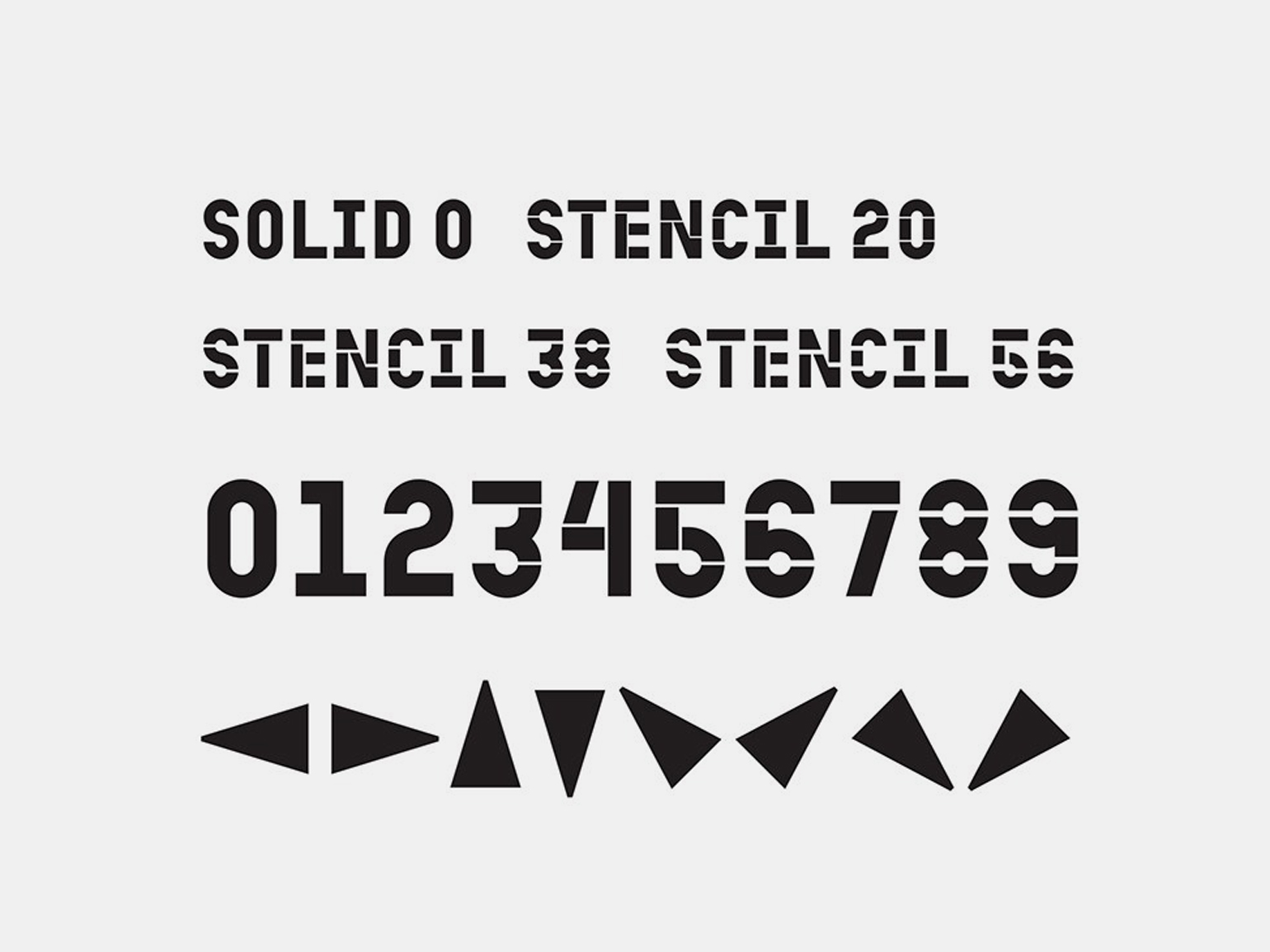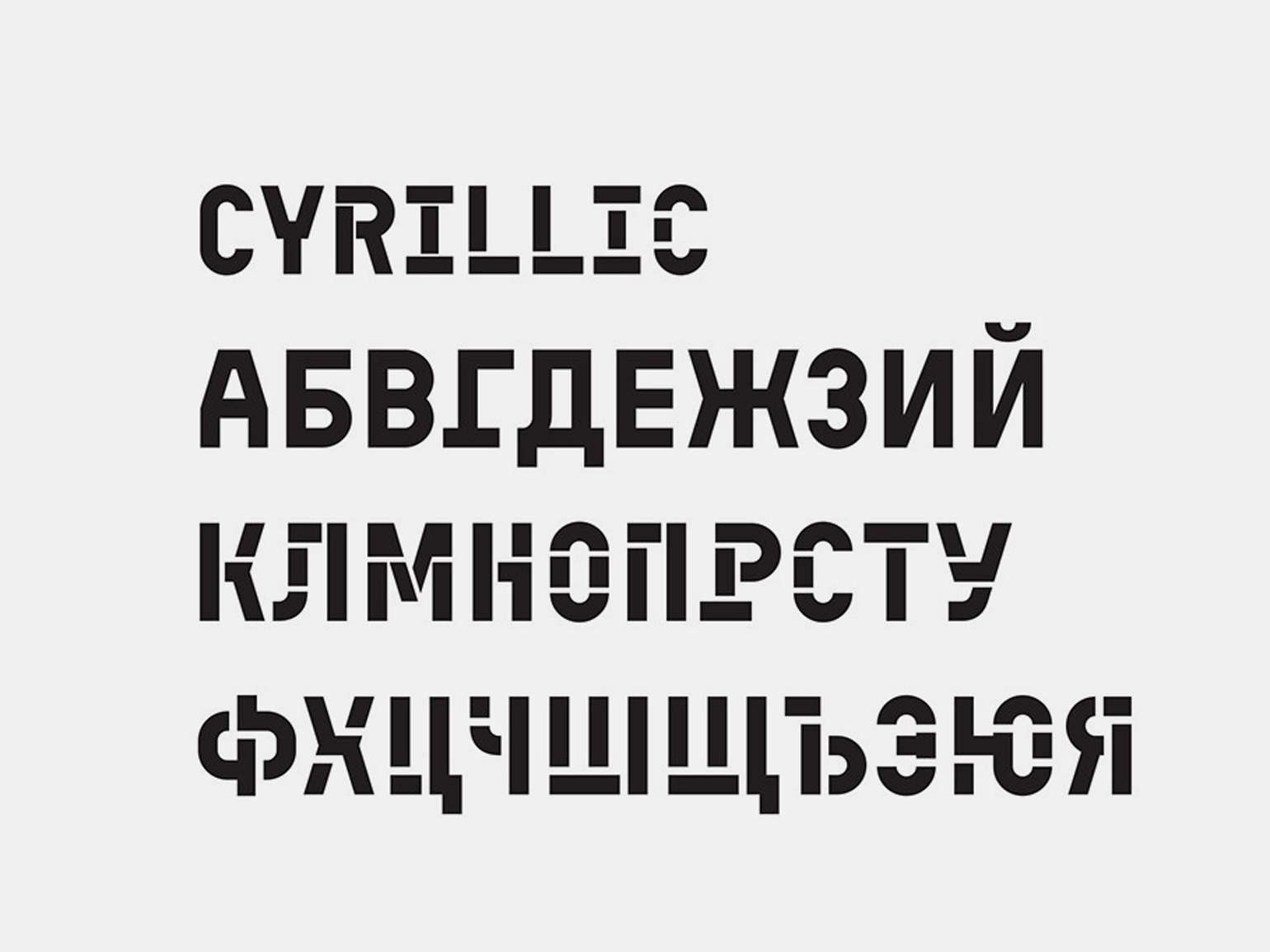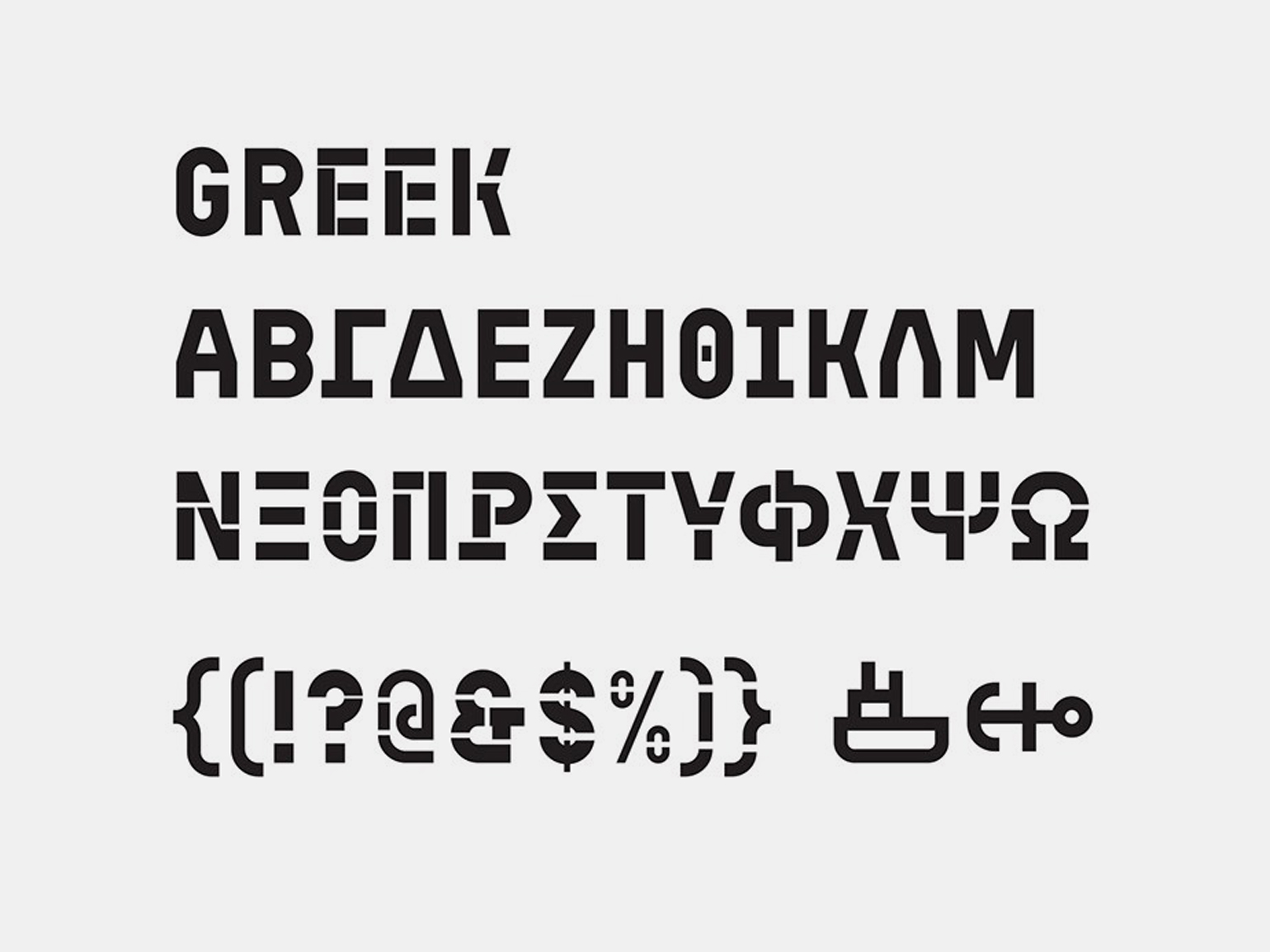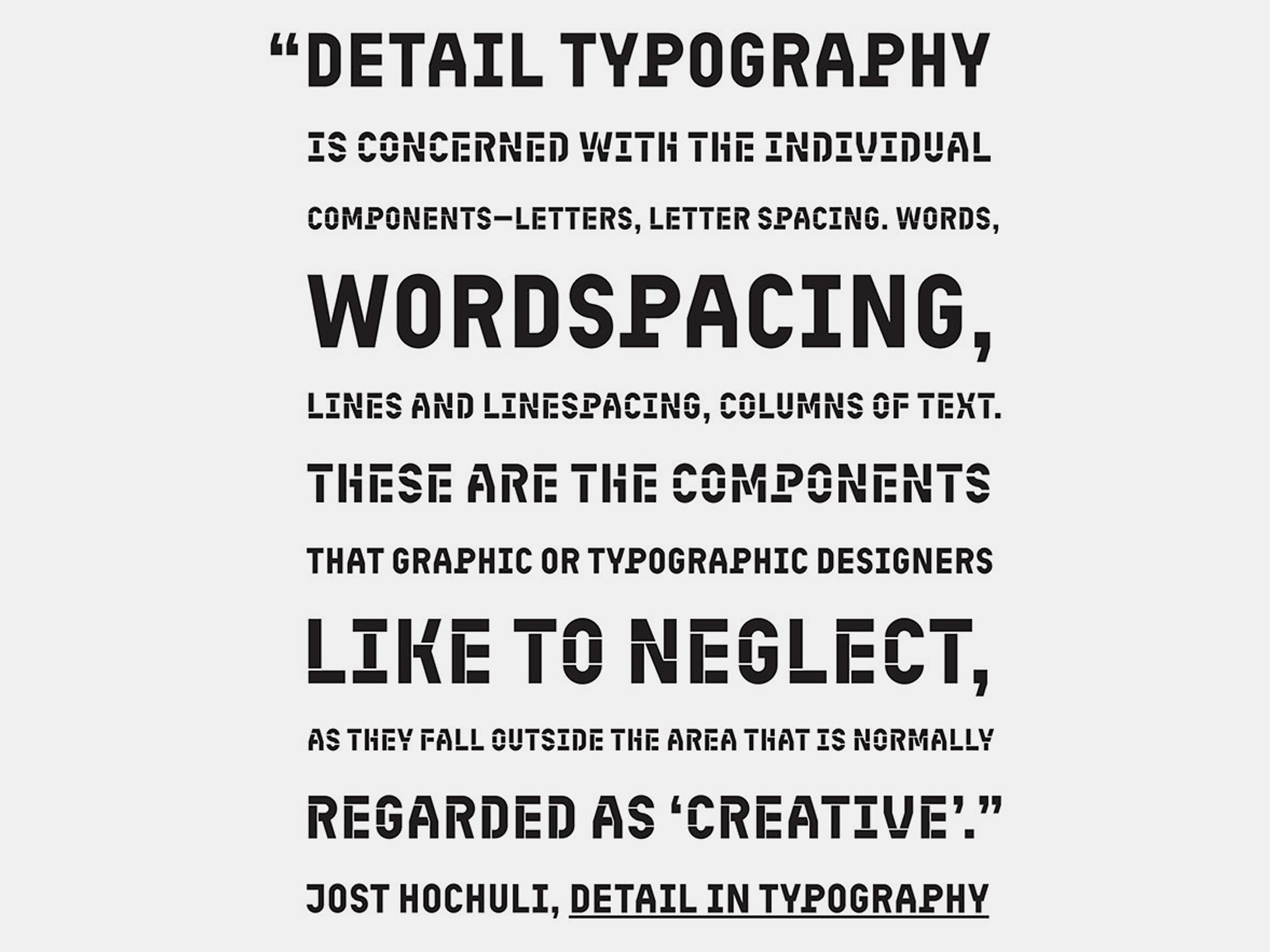
Шрифт Kabeltouw студии CoFo стал лауреатом премии Communication Arts
Он напоминает о мореходном деле и трафаретных надписях на контейнерах и буксирах.
Communication Arts — крупнейший международный дизайнерский журнал. Он был основан в 1959 году. Ежегодно Communication Arts проводит конкурс в шести категориях. Одна из них — типографика. В 2024 году в список лучших шрифтовых работ вошёл шрифт ​​студии Contrast Foundry. Мы попросили рассказать о нём его создателя Егора Головырина.
«Мне нравится относиться к шрифту как к материальной, а не как к цифровой вещи. Даже заведомо диджитальный проект я начинаю с каллиграфии, маркерного рисунка или вырезания из бумаги. Так же получилось и с Kabeltouw. Мне нужны были трафаретные формы для вывески. Я вырезал три картонных модуля: полукруг, прямую и диагональ — и сложил из них все нужные буквы.
CoFo Kabeltouw
В шрифтовой редактор „Кабельтов“ попал, когда я работал над своим дипломным проектом в Полиграфе (Московский Политех. — Прим. автора), книгой „Горизонт“ о морской терминологии, узлах, сигнальных флагах.
В качестве основного рабочего шрифта я сразу выбрал William Text Pro Марии Дореули, но хотелось поддержать красочные оттенки и плёночные фотографии яркой шрифтовой графикой. Тут я и вспомнил про свою тогда ещё безымянную трафаретную кассу. Пазл сложился: на морских контейнерах, предупреждающих знаках, буксирах очень часто можно увидеть такие брутальные буквы. Металл, краска, цвет — всё что нужно!
CoFo Kabeltouw
Позже добавилось второе начертание, монолитное. Уже в рамках работы в CoFo я добавил шрифту вариативность, чтобы дизайнер мог выбирать ширину трафаретных перемычек, нужную для дизайна и масштаба макета.
Я редкий участник конкурсов, а Kabeltouw — первый из моих выпущенных в свободную продажу шрифтов, так что в этот раз всё очень здорово совпало.
CoFo Kabeltouw
Создание шрифта — небыстрый процесс. Основная креативная работа занимает несколько часов или даже минут в начале, а до релиза может пройти несколько лет. Нужно расширять знаковый состав, делать техническую работу, заниматься другими проектами. Какие-то шрифты приходят раньше своего времени, какие-то опаздывают. Победы в конкурсах дают надежду, что набор родился ровно тогда, когда нужно», — рассказал дизайнер.
CoFo Kabeltouw